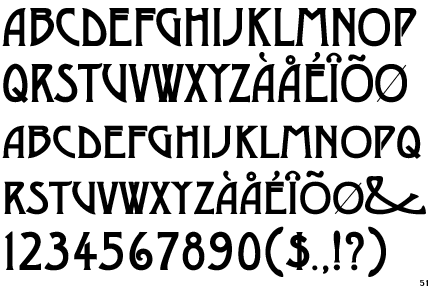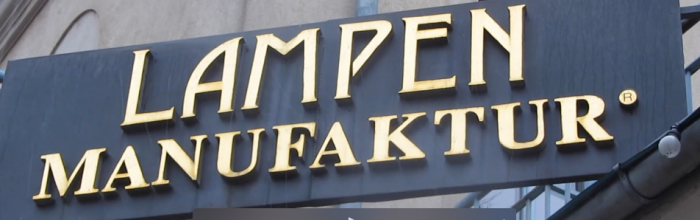
Jugendstilschrift gesucht
Auf dem Körnerplatz in Dresden gibt es schon seit ewigen Zeiten die Lampen-Manufaktur. Im Firmenschild ist das Wort Lampen in einer Jugendstilschrift gesetzt. Weiß jemand welche Schrift das ist. Vielen Dank.
Desdemona Black
Year: 1994
Publisher: BeattyType
Gewissermaßen die «gefüllte» Version der Desdemona © 1992 The Font Bureau, Inc.?
mir hat die Erklärung zur Schrift einfach nicht gefallen. Da fehlte fast ein Jahrhundert ... Viel besser sieht es aber so aus:
Quaint Gothic SG
Designer: Jim Spiece
Year: 1900,2002
Copyright: Spiece Graphics
Publisher: Spiece Graphics
Based on the Quaint Series from the Dickinson Type Foundry in Boston USA circa 1900. Also known as Desdemona by the K.K. Hof & K. Brendler Foundry.
Haben die offenbar (beim Luc?) falsch abgeschrieben, richtig wäre natürlich:
K.K. Hof-Schriftgießerei Karl Brendler und Söhne, Wien
Korrektur: K. und K. Hof-Schriftgießerei Carl Brendler & Söhne, Wien
Quelle: Liste der k.u.k. Hoflieferanten 1899
Brendler Carl, Schriftgießer und Graveur; Firma: Carl Brendler & Söhne.
Die Staatsbibliothek Berlin führt ihn unter "Karl Brendler und Söhne, K.u.K. Hof-Schriftgiesserei und Hof-Gravieranstalt (Wien)"
Correctur der Korrektur:
Das später eingefügte «u.» zwischen «K. K.» (bzw. «k.k.», «K.k.») hat rechtsgeschichtliche Gründe, es spiegelt nämlich die Verfassung des Staates wider.
Zuerst nämlich «Kaiserlich Königlich», später dann (und zwar wegen der geänderten staatsrechtlichen Stellung Ungarns — das wird sogar in der «Sissi»-Filmreihe thematisiert! ;-)) «Kaiserlich und Königlich».
Gleichwohl haben immer wieder manche Unternehmen, um gerade auf ihr Alter bzw. das frühe Datum ihrer Privilegierung hinzuweisen, später bewusst anachronistisch auf die ältere Version «K.K.» zurückgegriffen.
[bei «Carl» vs. «Karl» — eher eine Modefrage, wie man das schrieb.]